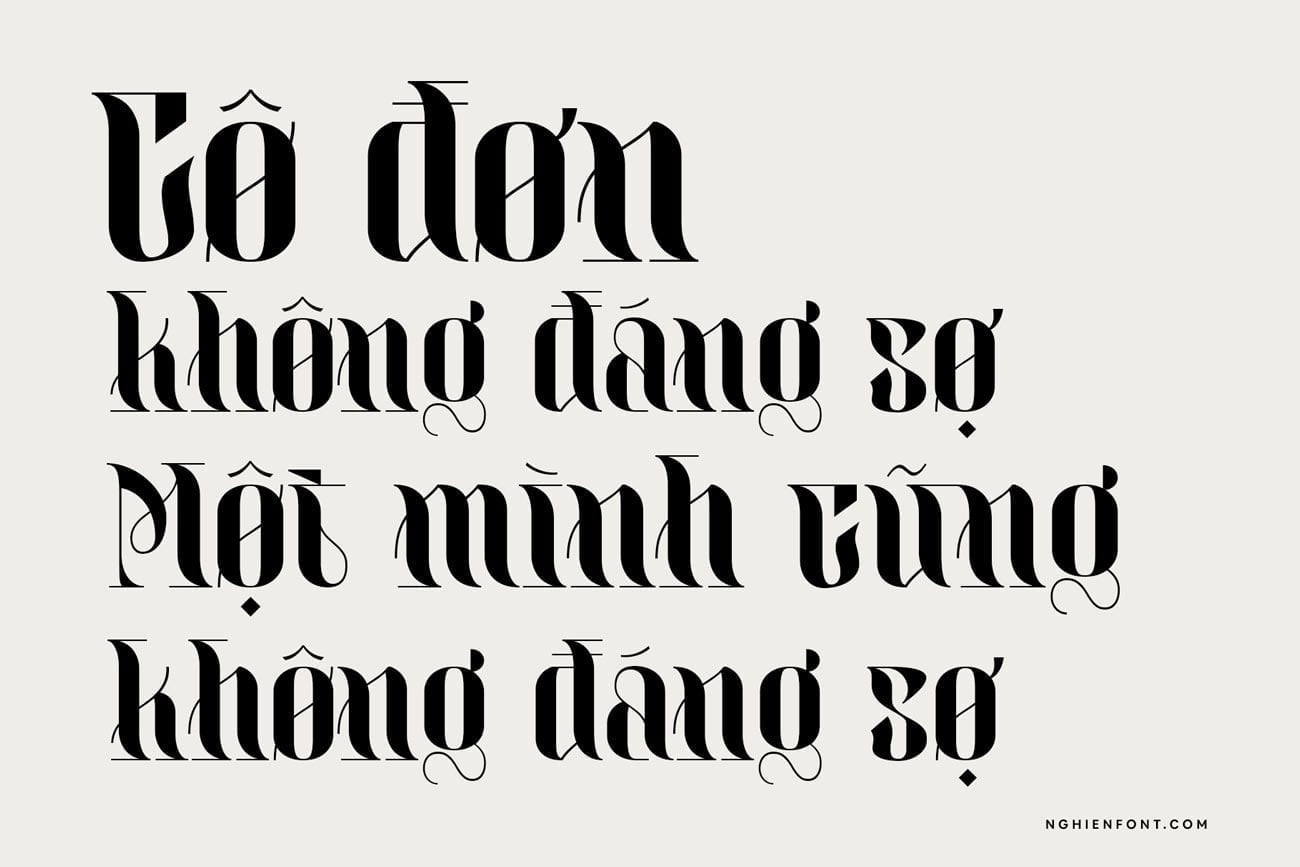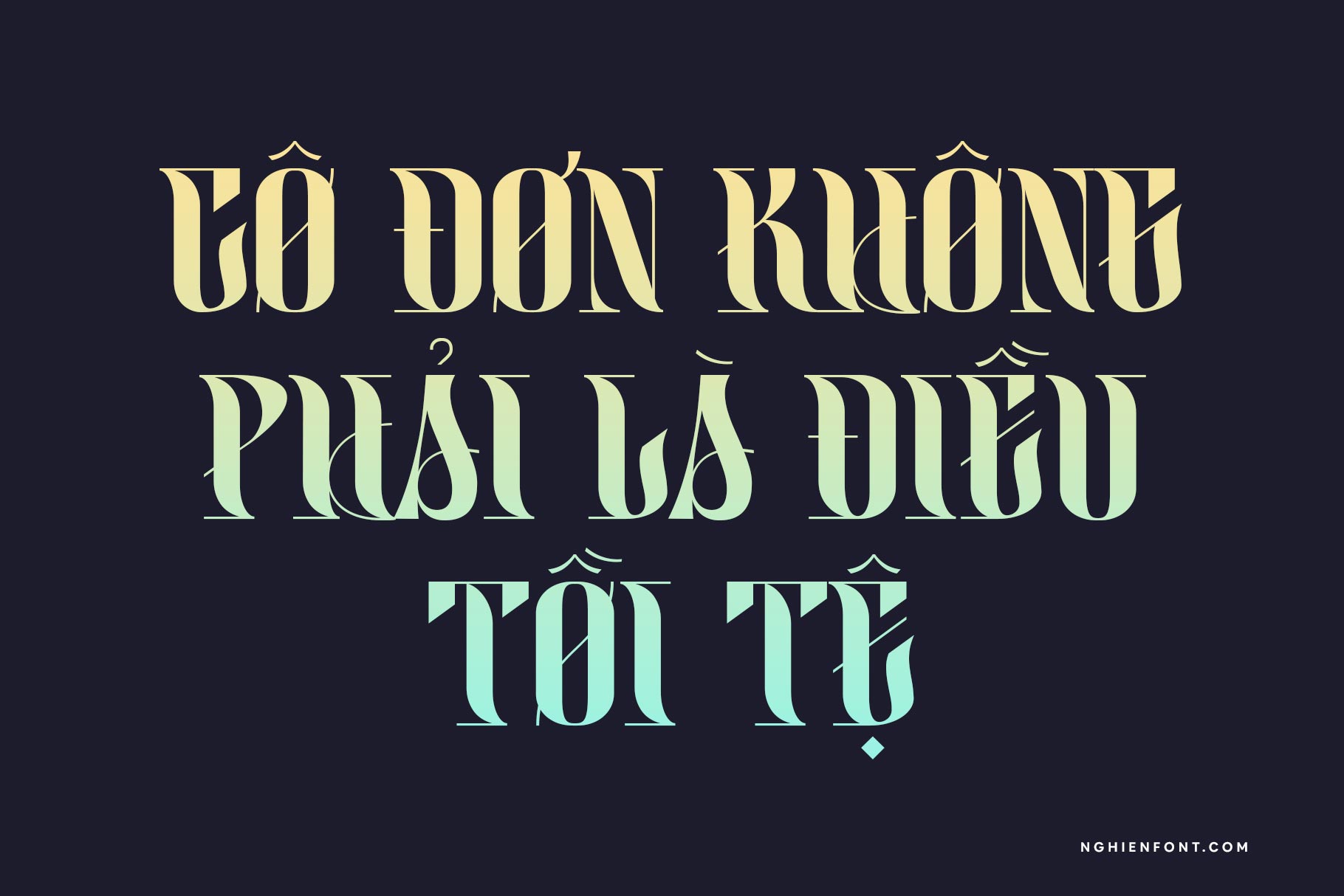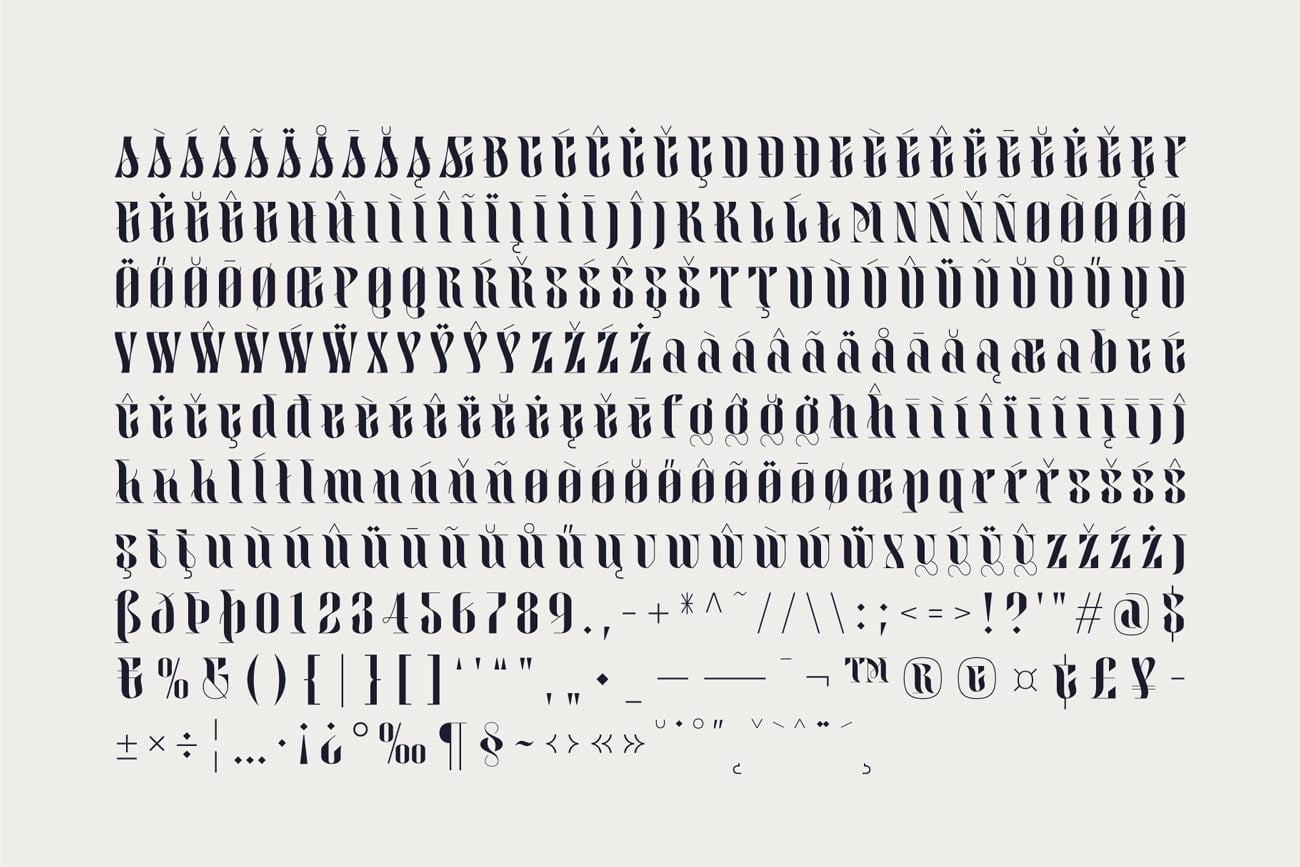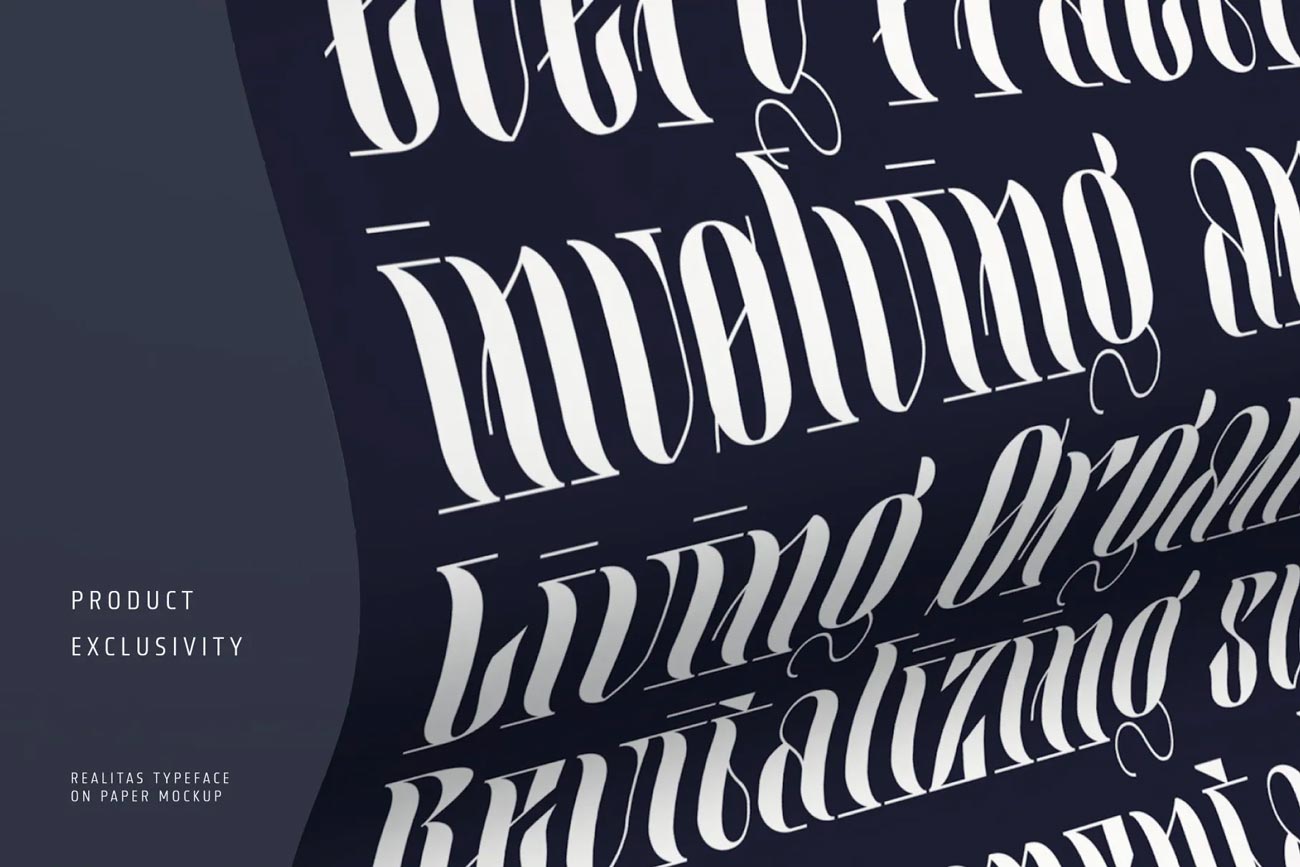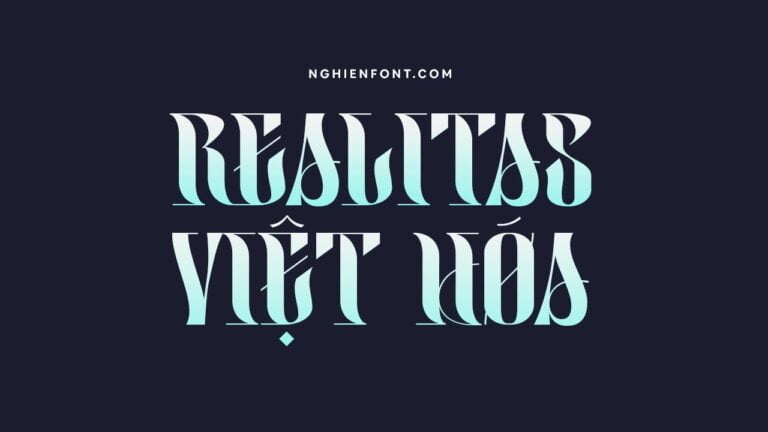
LNTH Realitas là một phông chữ hiển thị hiện đại và độc đáo được thiết kế bởi Eko Bimantara. Nó được tạo ra với mục đích khám phá những ranh giới mới trong thiết kế dạng chữ, tạo ra một kiểu chữ vừa đậm vừa đẹp mắt.
Font với hơn 300 glyph và hỗ trợ nhiều ngôn ngữ khác nhau, đây là một lựa chọn hoàn hảo cho các nhà thiết kế muốn một kiểu font hiện đại và cá tính.
Realitas là một ví dụ hoàn hảo về việc khám phá những ranh gưới mới có thể mang lại điều gì đó thực sự đáng chú ý. Thiết kế độc đáo và mang tính khám phá của nó khiến Realitas khác biệt so với các phông chữ hiển thị khác trên thị trường, khiến nó trở thành một bổ sung có giá trị cho bộ font của bất kỳ nhà thiết kế nào.
Font LNTH Realitas việt hóa phù hợp cho nhiều thiết kế như xây dựng thương hiệu, thiết kế logo, tạp chí, điện ảnh, thiệp mời, trang trí hoặc bất kỳ thiết kế nào khác.